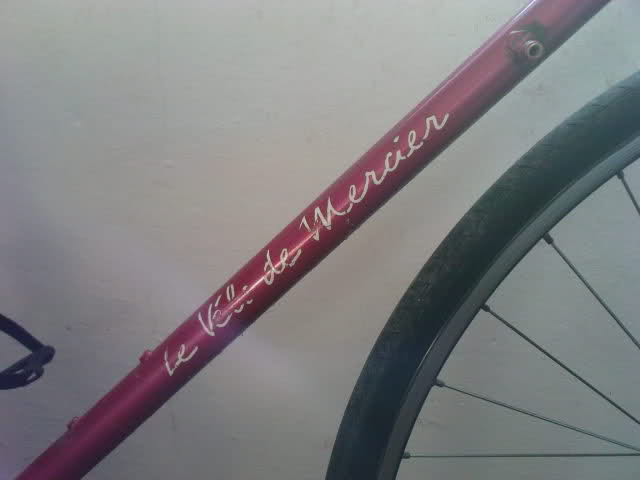
Schriftart von einem Fahrrad
ich suche mich im Internet dumm und dusselig nach einer Schriftart
aber kann nirgends passendes finden.
Sie stammt von einem Rad aus den 80ern.
Vielleicht habt ihr ne Ahnung?!
Bei so vielen verschiedenen "e" würde ich davon ausgehen dass sie mundgebissen ist.
Was genau heißt "Mundgebissen"?
Eigentlich sind die "e" ziemlich gleich.
Hab das vom Rahmen abgepaust; vielleicht deswegen die unterschiede?!
Hier noch das Original.
… Was genau heißt "Mundgebissen"? …
das heißt einfach nur dass das ein gezeichnetes Logo ist und aus keinem Font erstellt wurde. Also handgezeichnet, fußgemalt, handgeschnitzt, getöpfert, …
Das ist nich so schön zu hören.
Eine Rekonstruierung wird dadurch nicht leichter.
Bleibt mir wohl nur der Weg über die Vektorisierung...
Du koenntest Dich ja auch bei MyFonts durch die Handschriften wuehlen. Aehnliches gibt's da durchaus.
hab mich durch die 2000? oder was weiß ich wie viele
Schreibschriften gequält.
Etwas ähnliches habe ich schon gefunden. Aber dieses "M" ist wohl sehr charakteristisch; das passt nirgendswo so richtig.